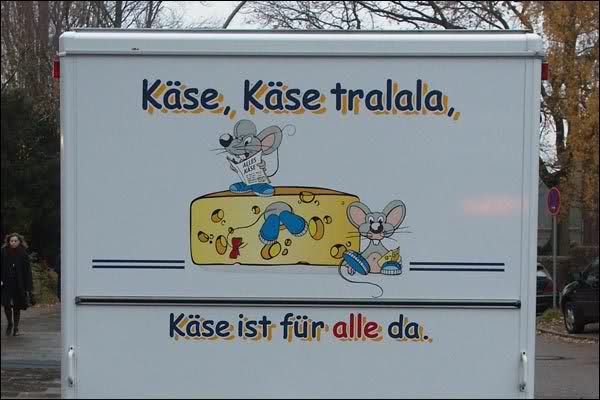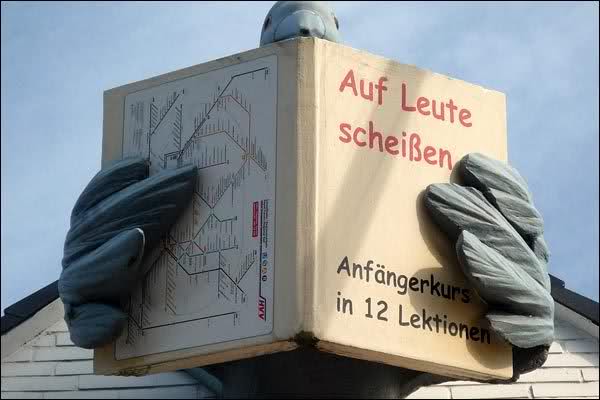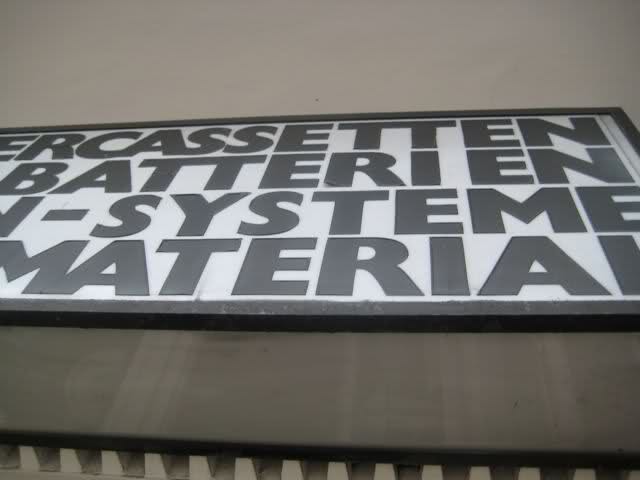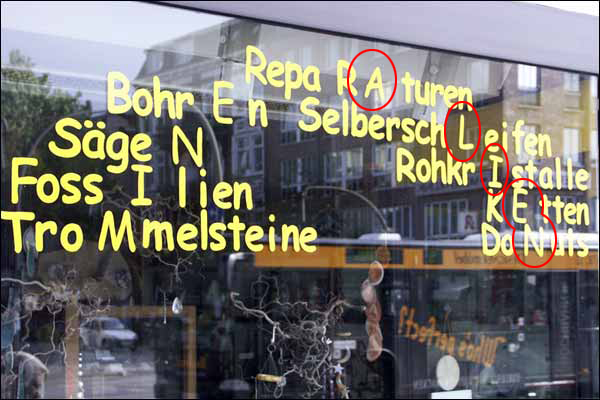
Typostreifzug durch die Stadt ...
Das mit dem Wappen-O ist mir zum ersten Mal über den Weg gelaufen, ich glaube eigentlich nicht, dass das verbindlich ist.
figelinscher
:lach: »figelinsch« ist auch Plattdeutsch. Könntest Du übersetzen mit: büschen komplizierter oder trickreich :) Ok, ich höre auf damit :wink:
Und das kann man steigern?! Figelinsch — figelinscher — am figelinschesten? Oder heißt das figelinschigst? Dies war das figelinscheste Problem, mit dem ich je confrontiert wurde? :o
:lach: »figelinsch« ist auch Plattdeutsch. Könntest Du übersetzen mit: büschen komplizierter oder trickreich :)
Nachtrag:
>> Mich erinnert "fikumdik" an "fiegeliensch".
>> figgeliensch? figelinsch? Oder gar mit "v"?
>> Ich habe keine Idee, wie dieses Wort geschrieben wird.
> Interessant. Was in etwa bedeutet es? In welchem Dialekt kommt es
> vor?
Nach meiner Erfahrung ist dieser Ausdruck zumindest im
norddeutschen Raum (Schleswig-Holstein, Hamburg, Niedersachsen)
nicht ungebruchlich. Es bedeutet pfiffig, schlau.
Und das kann man steigern?! Figelinsch — figelinscher — am figelinschesten? Oder heißt das figelinschigst? Dies war das figelinscheste Problem, mit dem ich je confrontiert wurde? :o
Ich würde sagen: figelinscheste
Und das kann man steigern?! Figelinsch — figelinscher — am figelinschesten? Oder heißt das figelinschigst? Dies war das figelinscheste Problem, mit dem ich je confrontiert wurde? :o
Ich würde sagen: figelinscheste
Na immerhin hat dieser Thread den Vorteil, daß demnächst auch die Datenkrake dieses Wort kennen wird.
Na ja, wenn Du »figelinsch« eingibst, bekommst Du auch jetzt schon ein paar Antworten. :)
Da kannst Du auch mal unter »Missingsch« kucken. Reines Plattdeutsch bekommt man heutzutage nämlich nur noch selten zu hören. Eher Missingsch, oder – in den meisten Fällen –
ein mit plattdeutschen Wörtern durchsetztes Norddeutsch. :)
Ich war am Wochenende mal ein bisschen Buchstaben sammeln … :)
So richtig schrecklich wird es aber erst, wenn die Grindelallee zur Hoheluftchaussee wird ...
Wenn man dann noch ein Stück weiter stadtauswärts fährt, dann bekommt man solche Dinge – in der Kollaustraße – zu sehen ...
Aber auch Alsterdorf ist ein interessanter Fundort ...
Handarbeit :wink:
Das finde ich toll! Zumindest den Teil in der Gill Sans Ultrabold. Schon allein die Wortwahl.
Leercassetten, Elektromaterial, Gelegenheiten und mein Liebling: Rasiererzentrale :biglove:
Das ist eine geheime Botschaft aus dem All … lest die Versalien …
Lach, ach cool Bertel, ok verstanden, Mineralien. So genau hatte ich gar nicht draufgeschaut. Sehr subtil und feingeistig umgesetzt :wink:
Oben zu lesen angefangen ergibt sich ja "ALIEN", was ich noch viel tollerer find :mrgreen:
Ja, habe ich gesehen. :wink: Das ist in der Tat noch subtiler … Vielleicht kaufen da ja auch hauptsächlich Außerirdische ein. Bei dem überirdisch schönen Schaufensterdesign … :)
jedesmal, wenn ich da auf den bus warte, frage ich mich, ob sie das kleine s verkehrtrum aufgeklebt haben. zudem macht das ganze den eindruck, als ob die das mit pakettesa zusammengekleistert hätten.
Handarbeit :wink:
Das finde ich toll! Zumindest den Teil in der Gill Sans Ultrabold. Schon allein die Wortwahl.
Leercassetten, Elektromaterial, Gelegenheiten und mein Liebling: Rasiererzentrale :biglove:
Finde ich auch extrem cool. Das ist am Grindel? Ist mir noch nie aufgefallen ... :?
Ich glaub ich muss morgen auch mal durch die Stadt und ein Paar Fotos machen, habe da schon was ganz schönes im Kopf, was ich Euch zeigen muss. :)
Ja genau, Grindelallee, wenn Du von »2001« auf der linken Straßenseite Richtung Hoheluft gehst. :)